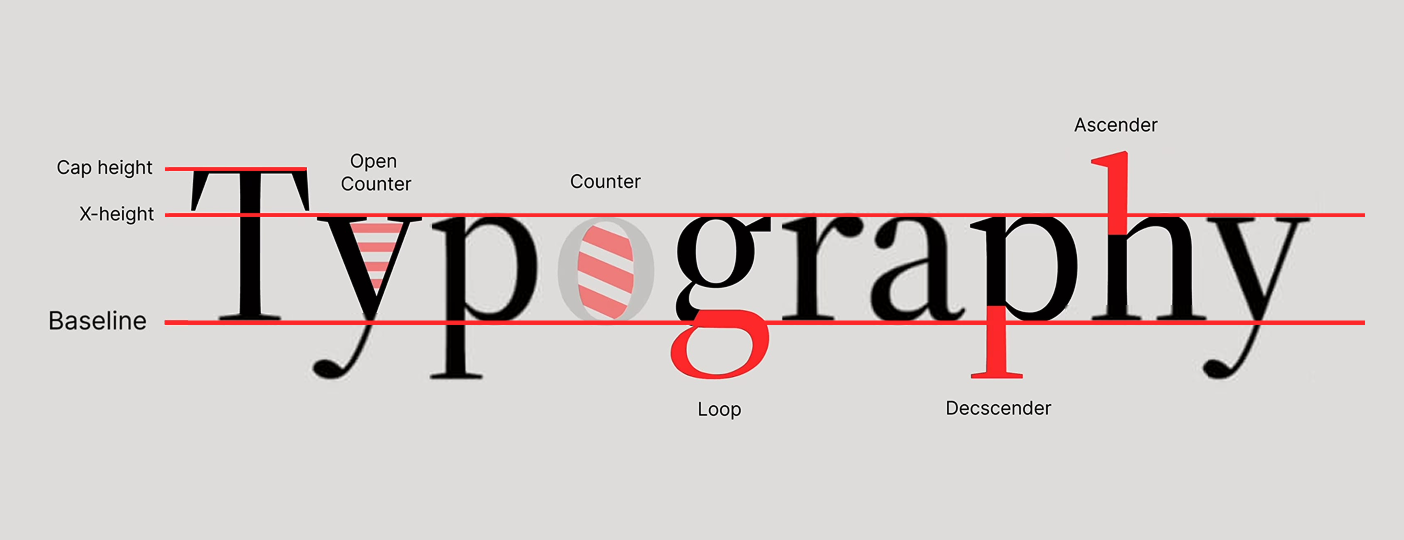
Cum alegi fonturile potrivite pentru UI:Ghid practic de tipografie
Alegerea fonturilor nu ar trebui să fie un joc de noroc prin selectorul de fonturi. Majoritatea designerilor se opresc la ceea ce „arată bine la prima vedere”, dar fără să înțeleagă de ce. Pentru a lua decizii mai bune, trebuie să cunoști anatomia tipografiei și felul în care aceasta influențează lizibilitatea și echilibrul vizual în UI design.
Pasul 1: Înțelege liniile de bază
• Baseline – linia invizibilă pe care stau literele. Ea oferă structură și consistență textului.
• Line-height – spațiul dintre două baseline-uri consecutive; crucial pentru respirația vizuală.
Pasul 2: Cunoaște părțile literelor
• Descender – partea literei care coboară sub baseline (ex. „g”, „y”); ajută la lizibilitate.
• Ascender – partea literei care urcă deasupra x-height-ului (ex. „h”, „l”); echilibru și claritate.
• Stem – coloana vertebrală a literei, baza structurii.
• Loop – bucla închisă (ex. la „g” mic), adaugă personalitate.
• Serif – „pantofii și pălăriile” literelor; diferențiază fonturile serif de cele sans-serif.
• Counter – spațiul interior al unei litere (închis: „o”; deschis: „c”); influențează lizibilitatea la dimensiuni mici.
• Horizontal bar – liniile orizontale (ex. „T”), esențiale pentru echilibru vizual.
Pasul 3: Analizează proporțiile
• X-height – înălțimea literelor mici; definește lizibilitatea.
• Raportul dintre ascender și descender determină cum se „simte” un font într-o interfață.
Pasul 4: Gestionează spațiul dintre litere
• Kerning – spațiul dintre caractere individuale.
• Evită lacunele incomode sau suprapunerile – fiecare pereche de litere are propriile nevoi de spațiere.
Pasul 5: Testează fonturile în context
Nu alege doar din lista de fonturi. Rulează micro-teste cu text real din UI-ul tău – butoane, etichete, paragrafe – pentru a vedea cum se comportă fontul în situații diferite.